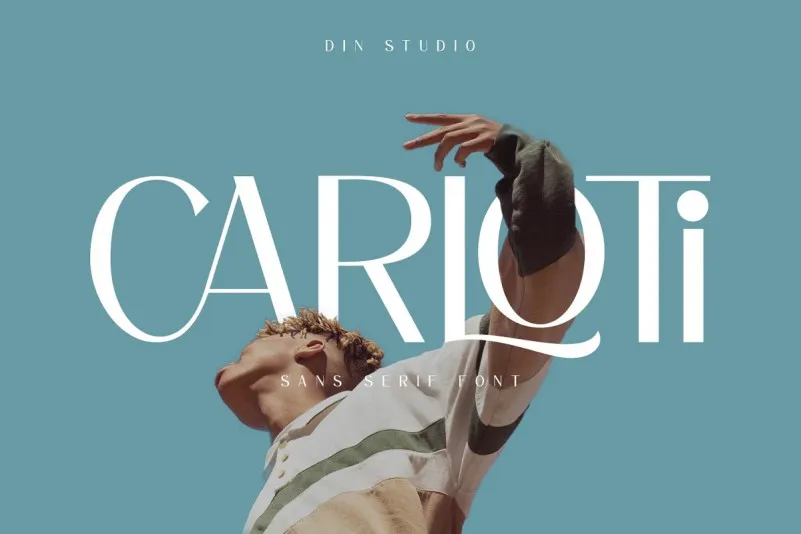
Carloti Font é uma elegante fonte de tipo sans-serif desenvolvida pela Din Studio. Esta opção exclusiva inclui alternativas para cada letra do alfabeto, oferecendo um design sofisticado e moderno que se ajusta a qualquer projeto. Carloti Sans Serif é perfeito para banners e postagens em redes sociais, como posts de mídia social e anúncios. Além disso, é adequada para frases impressas, desenhos de camisetas, embalagens, ou mesmo como overlay moderno de texto sobre imagens de fundo. Esta demo versão é gratuita para uso pessoal; se desejar mais opções ou comprar outros produtos e fontes, visite o seu marketplace para obter apoio ao designer.